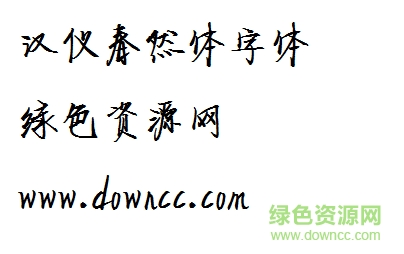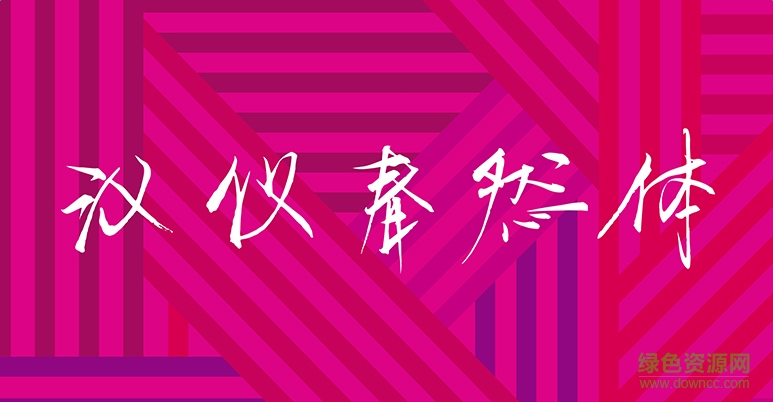
漢儀春然體是一款漢儀類(lèi)女性灑脫風(fēng)格字體軟件,春然體筆畫(huà)灑脫,整體效果顯得潦草有創(chuàng)意,比較有魅力,深受廣大女性喜愛(ài),還有更多好看字體歡迎來(lái)綠色資源網(wǎng)下載體驗(yàn)!
漢儀春然體是一款商業(yè)字體,瀟灑帥氣的女性風(fēng)格字體,筆畫(huà)隨意卻不失工整,非常有韻味!